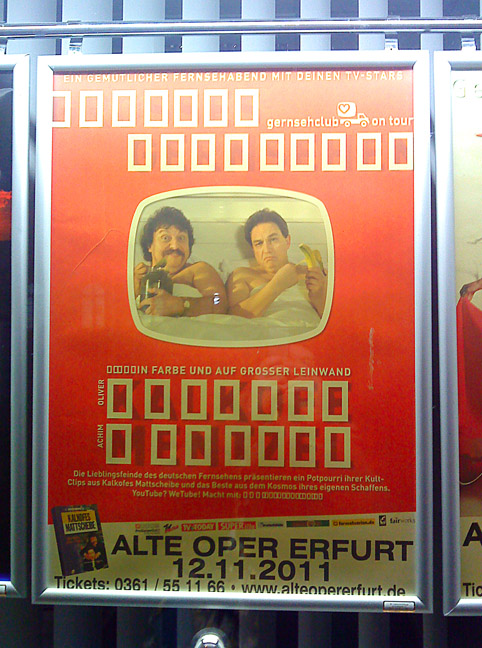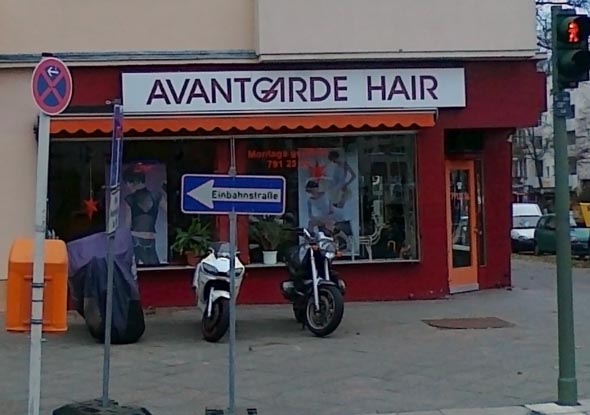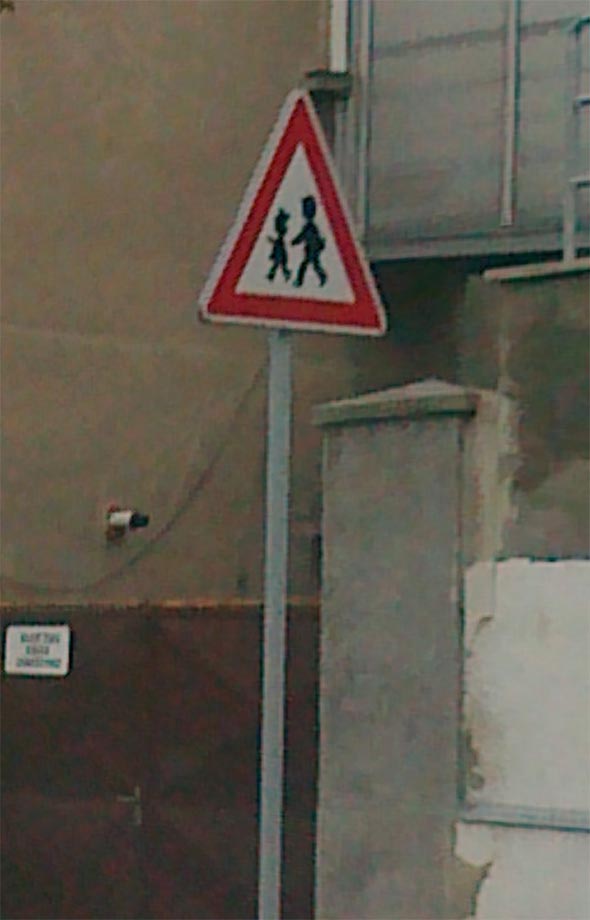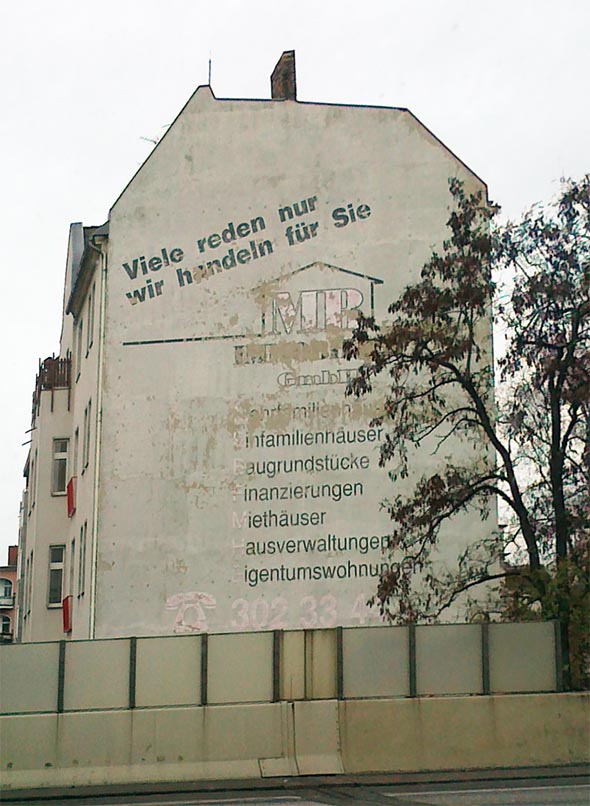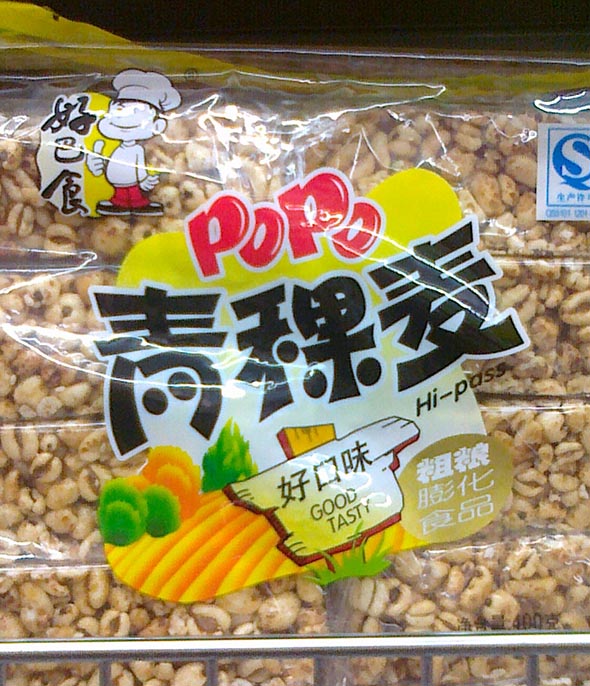
Finde auch, daß durch einen simplen Trick eine Zusatzinfo vermittelt wird ohne daß die ursprüngliche Information leidet. So kleine Pointen sind mir lieber als großes Geschrei.
Wenn es irgendwas mit dem Web zu tun hätte, könnte man fast schon geniale Absicht vermuten.So ist es natürlich nur peinlich.
Ansonsten wundere ich mich schon, dass sich (m.W.?) noch kein Web-Künstler »� �« oder so ähnlich genannt hat.
Hier ein weiteres Fundstück, und zwar ein etwa 60 × 31 cm² großes und knapp drei Kilogramm schweres Blechschild der Bleistift-Fabrik Eberhard Faber KG in Neumarkt bei Nürnberg:
Mir gefällt das kleine c besonders gut, aber auch das ä hat es in sich, wie ein Leser meines Blogs angemerkt hat. – Datieren kann ich dieses Schild leider nicht.
das menzel/kalkhofe plakat ist echt der hammer, wer gibt sowas raus?
Zum Warnhinweis: Bei einem batteriebetriebenen Milchaufschäumer konnte ich mal lesen:
Personen (einschließlich Kinder), die aufgrund ihrer physischen, sensorischen oder geistigen Fähigkeiten oder ihrer Unerfahrenheit oder Unkenntnis nicht in der Lage sind, das Gerät sicher zu benutzen, sollten dieses Gerät nicht ohne Aufsicht oder Anweisung durch eine verantwortliche Person benutzen.
Mein Ergänzungsvorschlag: Milch nicht im Mund aufschäumen.
Falls Du noch mehr solcher schönen Stilblüten aus Gebrauchsanweisungen gesammelt hast, würde die Sprachpflegegruppe sich freuen, Dich in ihren Reihen begrüßen zu dürfen. Neben Gestalterfloskeln, Politfloskeln und Behördensprech wäre Gebrauchsanleitungsprosa eine sehr willkommene Bereicherung.
Dieses Konstrukt vom Life Centre in Newcastle hat mich einigermaßen fasziniert. Während meines Aufenthaltes habe ich mich über das völlig verunglückte »f« gewundert. Bis mir am letzten Tag auf einmal aufging: das soll ein »f« und gleichzeitig ein Chromosom sein! Ich hatte das einfach nicht wahrgenommen. Ich habe daraufhin eine Freundin gefragt, welche erstaunt meinte: »Ach, ›life‹ soll das heißen? Ich habe das immer nur als Chromosom und nicht als ›f‹ wahrgenommen!« Andere Kollegen haben dies in ähnlicher Weise bestätigt. Alle sehen entweder ein »kindisches« f oder ausschließlich ein Chromosom. Als »hybrid« ist es zwar gut gemeint, funktioniert aber offenbar einfach nicht.
Seltsam. Auf Deinem Bild habe ich ebenfalls nur ein verunglücktes f gesehen, auf der Netzseite dagegen das Chromosom und als zweites ein x.
Ich habe dazu irgendwo noch ein kleines feines Buch im Regal – randvoll mit unglaublichen Gebrauchsanweisungen. Ich werde bei nächster Gelegenheit mal danach suchen.Zitat von Pachulke
Steven Heller and Louise Fili — Scripts
gerade angekommen. auf den ersten blick: tolles buch.
verschiedene scriptbeispiele aus werbung und schriftmustern, ist aufgeteilt in
british, german, french, italian und american. allerdings ein böser satzfehler bei der kapitelüberschrift
zu german: "Der Schrift"
Gab es hier nicht schon einmal einen Strang mit Beispielen von Geschäften, wo Schriftart und Bezeichnung übereinstimmen? Ich finde den gerade nicht. Photo oben aus Berlin.
Kann es ein, daß es nicht nur an der Qualität, sondern auch an der Namensfindung für das Produkt liegt, daß Kelloggs Smacks in Deutschland erfolgreicher sind als obiges Produkt?
Kreativität und Naturwissenschaft: Wenn man nicht einrechnet, daß Rot sich unter UV-Einfluß schneller abbaut als andere Farben, kann sich eine Hervorhebung, die am Monitor noch so schön knallig war, ganz schnell ins Gegenteil verkehren. Besonders an Façaden.
Die Sperrung steht doch ganz klar für die Entfernung: 30 Minuten weg: kaum gesperrt – 1,5 Stunden Weg: große Sperrung